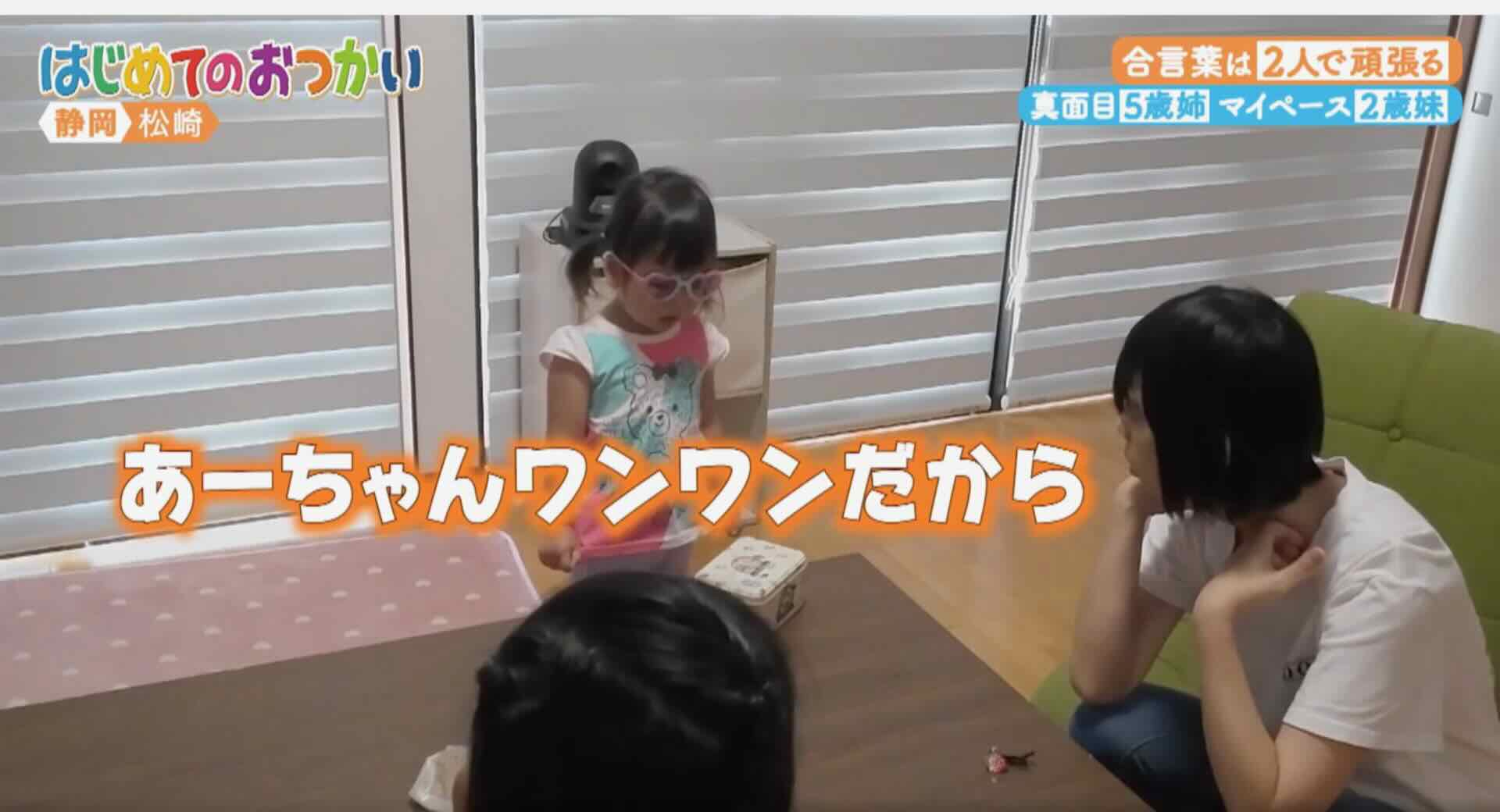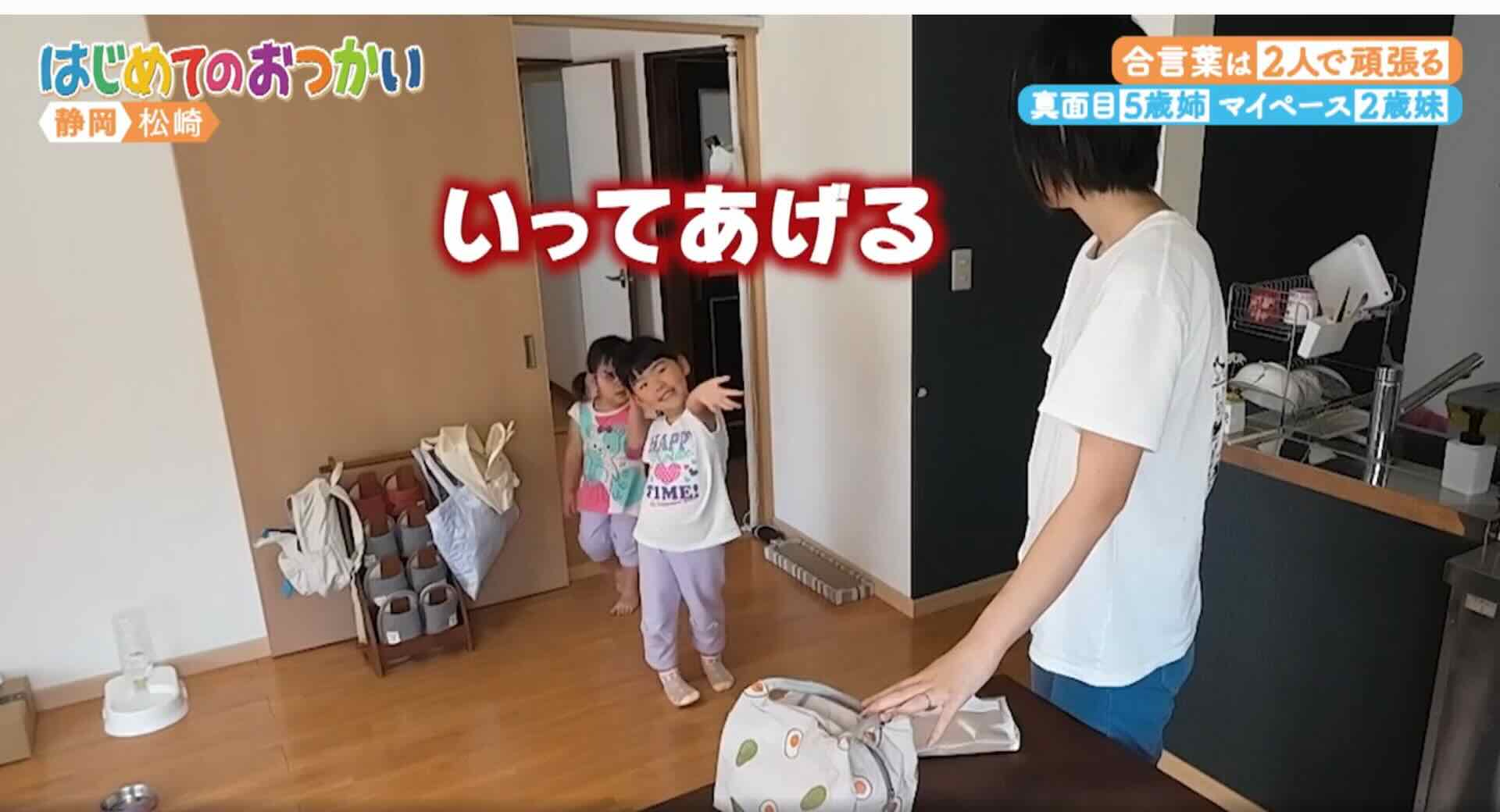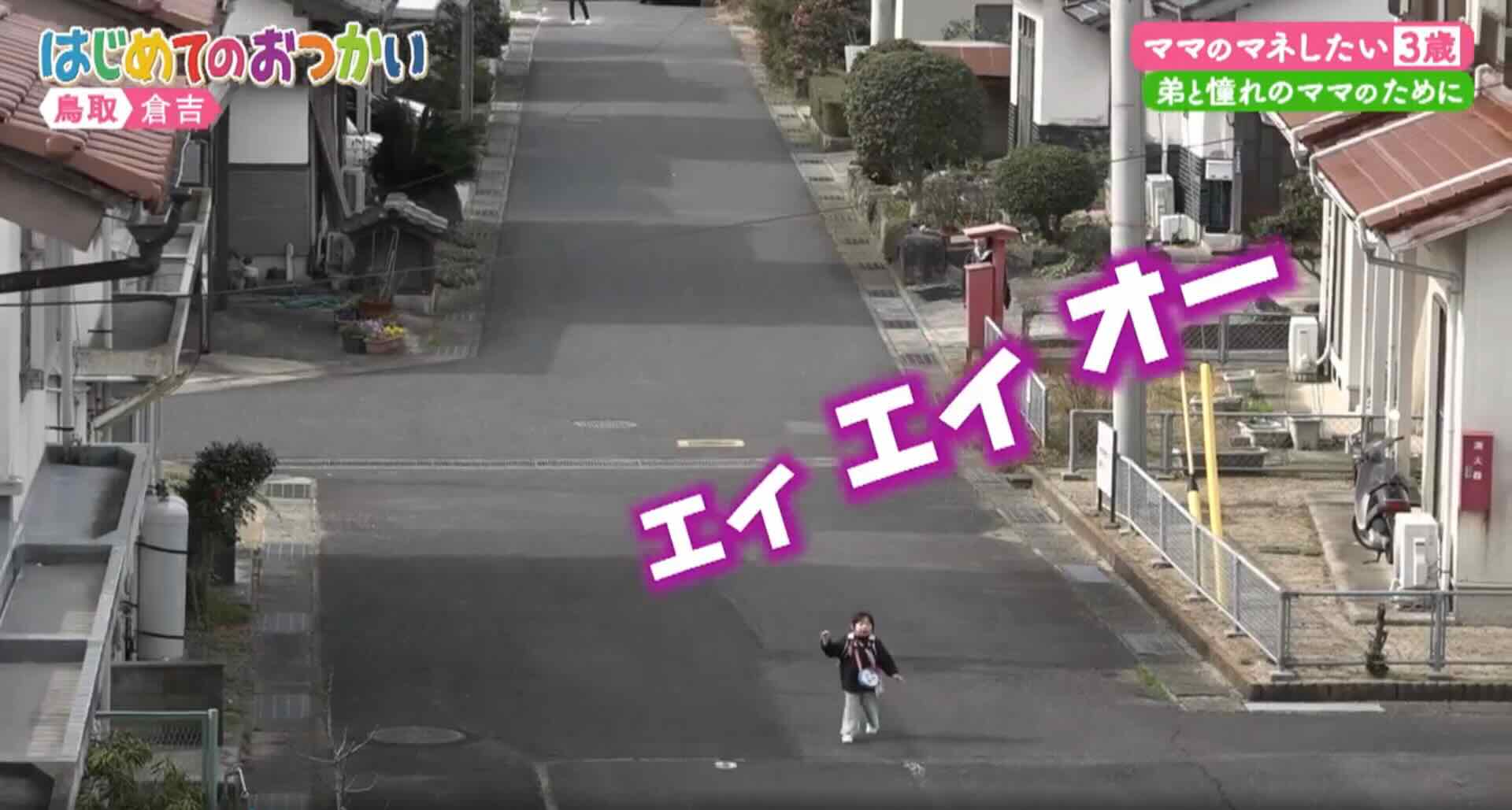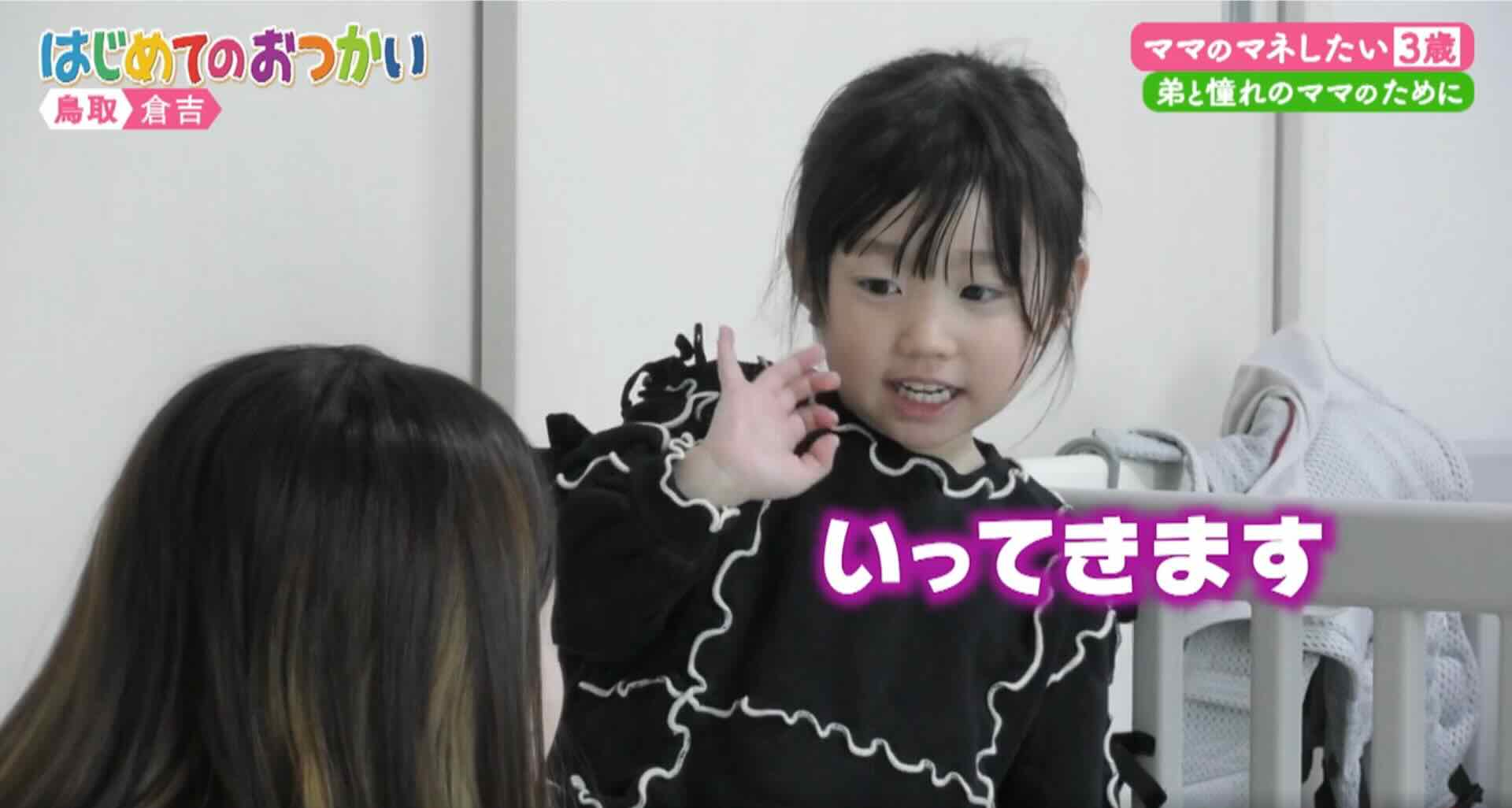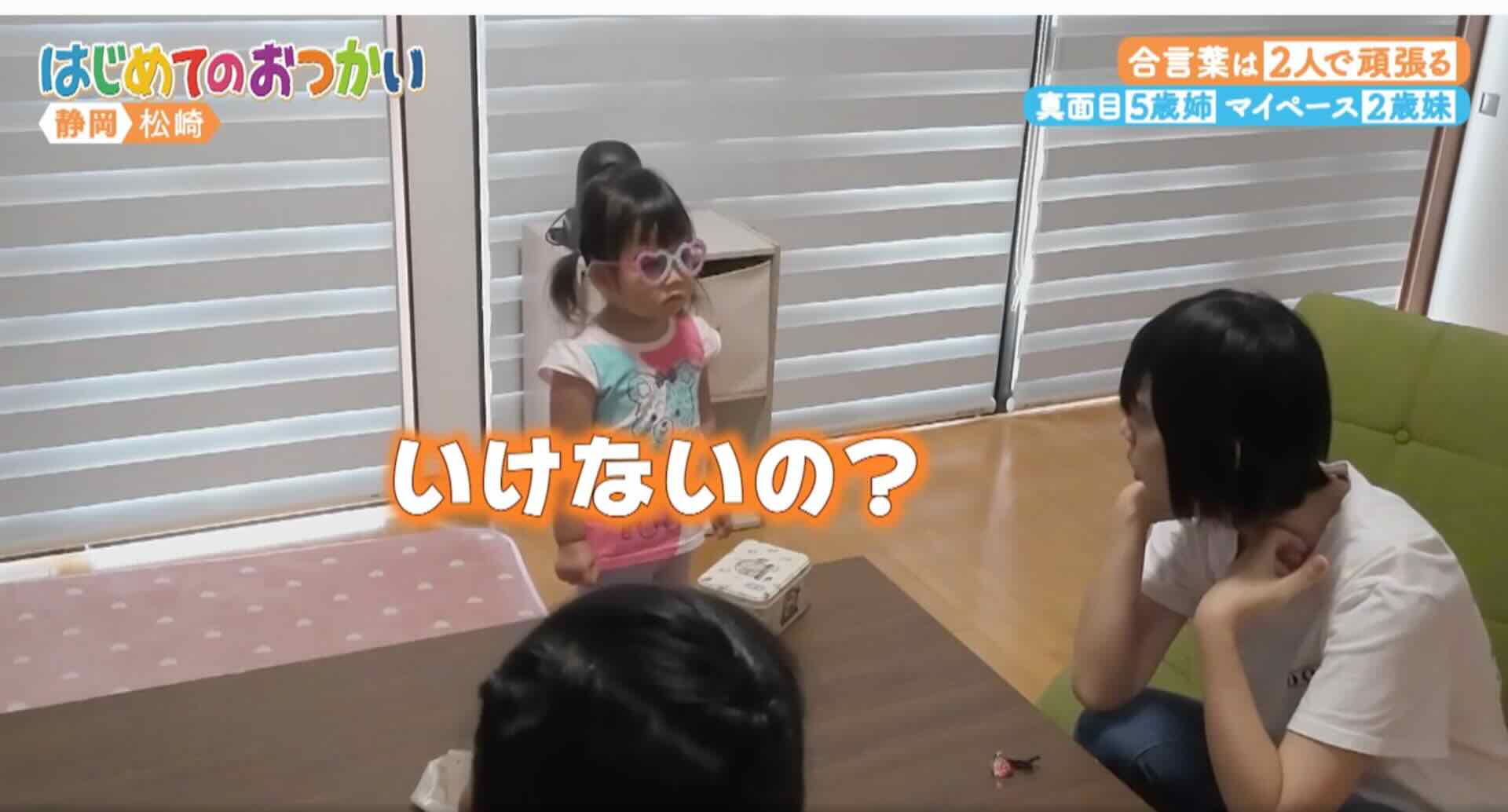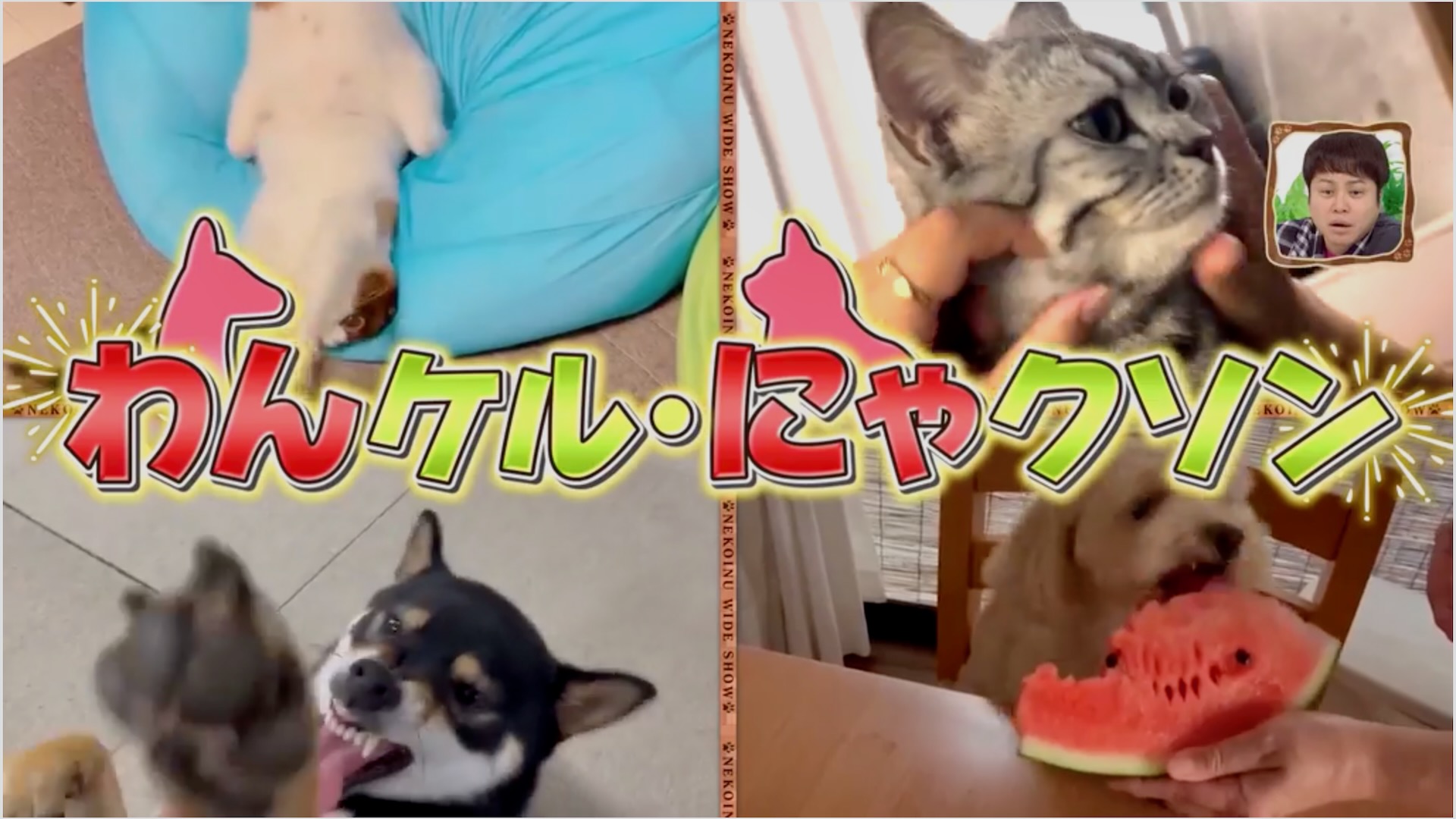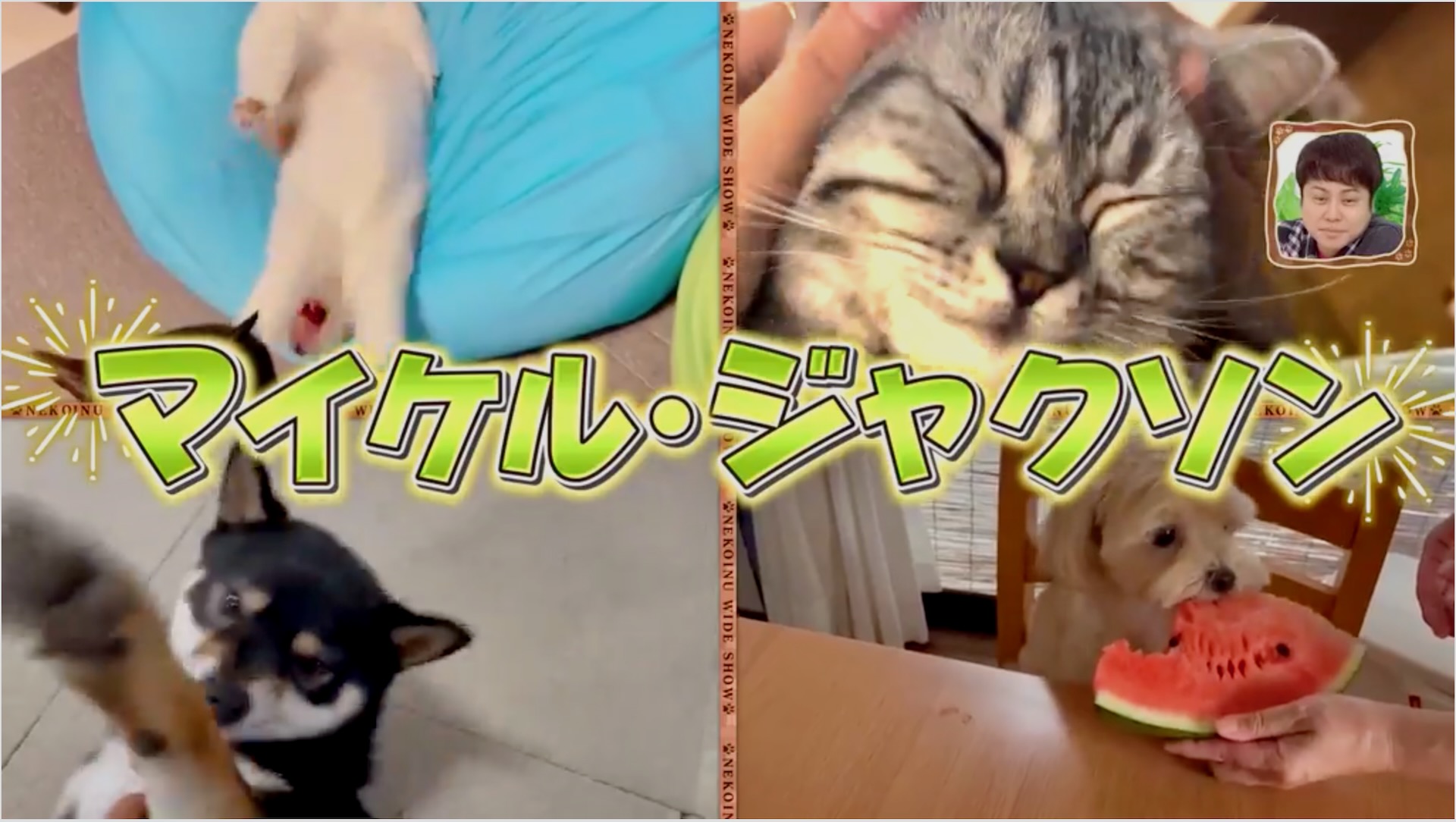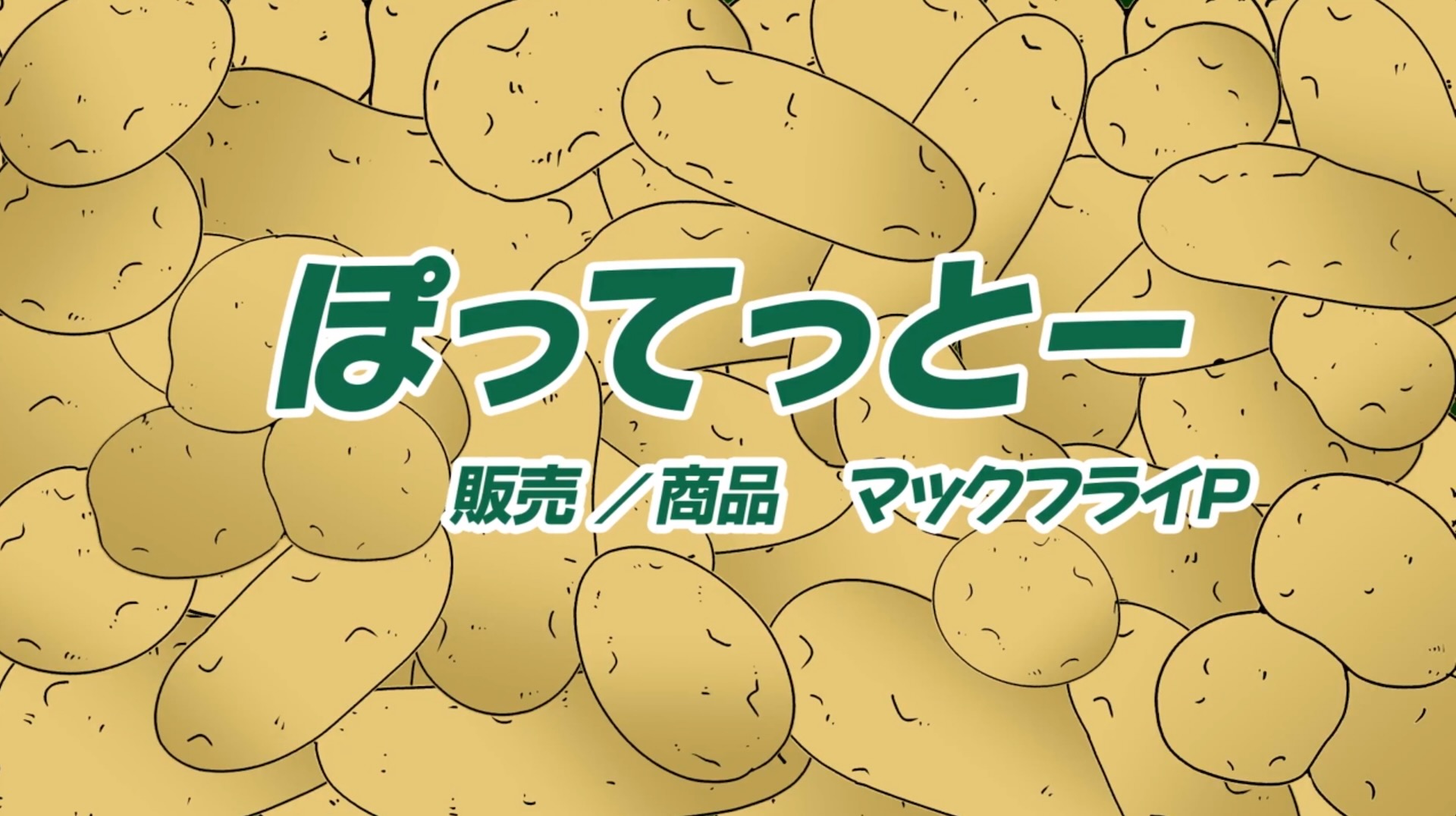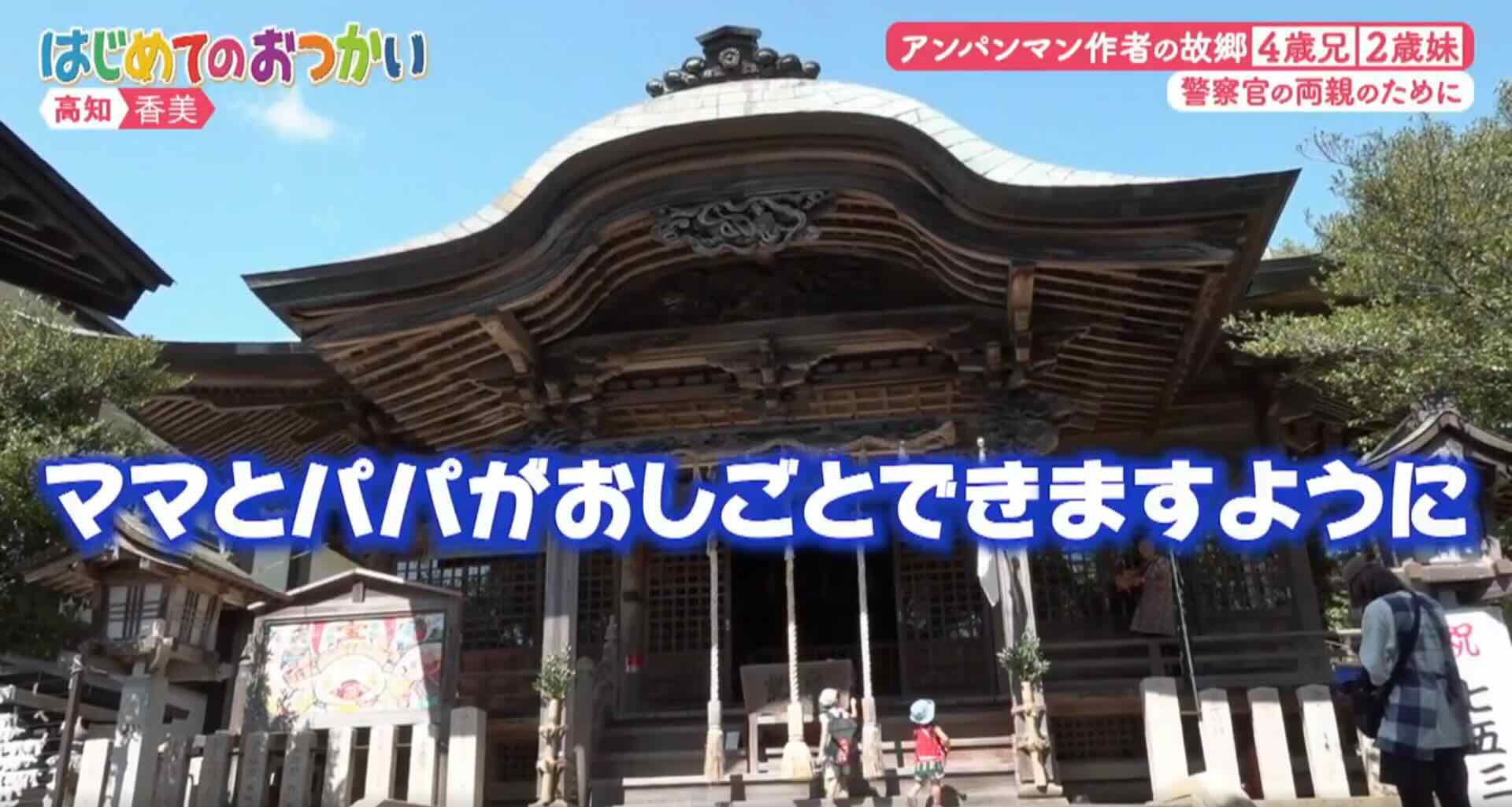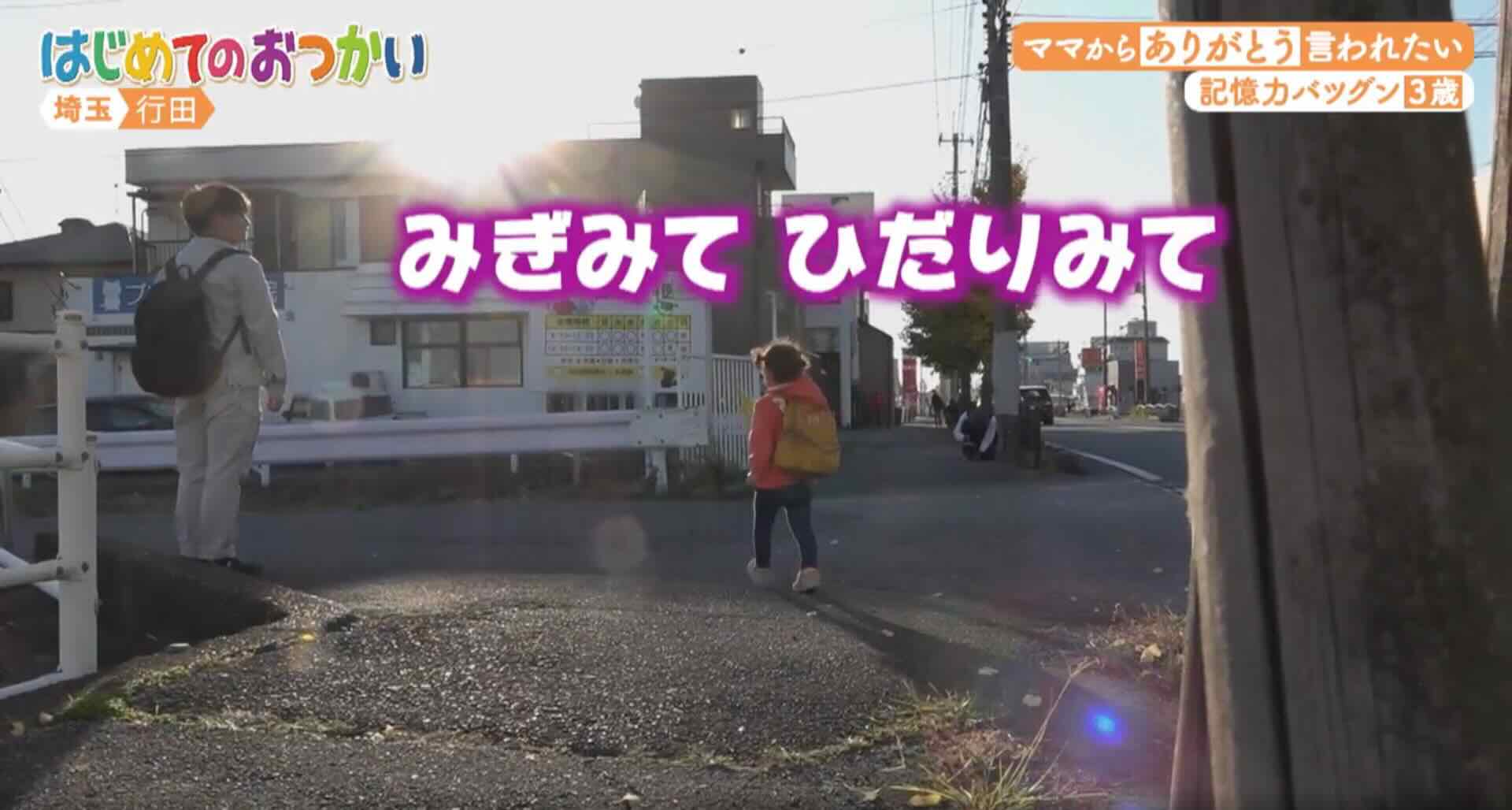
フォントワークスやモリサワから販売され親しまれている、かな書体「ハッピー」
人気テレビ番組 さとうゆたか
日本テレビ系列の「はじめてのおつかい」。
子供のセリフは、すべてハッピー書体のようだ。
店頭広告 さとうゆたか
誰でも知っている有名な筆記具。
全体像。
クレヨンしんちゃん さとうゆたか
人気アニメのサムネール画像。
テレビ番組 さとうゆたか
日本テレビ「はじめてのおつかい」。
アンパンマンのかみしばい さとうゆたか
書名:アンパンマンとばいきんまん
著者:やなせたかし
発行:フレーベル館
アンパンマンのとびだすえほん さとうゆたか
書名:こんにちは!
原作:やなせたかし
発行:フレーベル館
書名:のりもの
原作:やなせたかし
発行:フレーベル館
書名:どうぶつ
原作:やなせたかし
発行:フレーベル館
書名:わくわくびっくり!
原作:やなせたかし
発行:フレーベル館
本の表紙 さとうゆたか
書名:ポコポコ かくれんぼ
著者:NHKおかあさんといっしょ
発行:講談社
アニメのオープニング takumi
アニメ「タコピーの原罪」の第5話のオープニングで「ハッピー」が使われていました。
細めのハッピー書体が、きれいに使われていますね!
本の表紙 さとうゆたか
書名:たつくん おむかえドキドキ
著者:きむらゆういち【作】ふくざわゆみこ【絵】
発行:ポプラ社
クッキーラン:オーブンブレイク さとうゆたか
このゲームでは、ハッピールイカが全面的に使われているようだ。